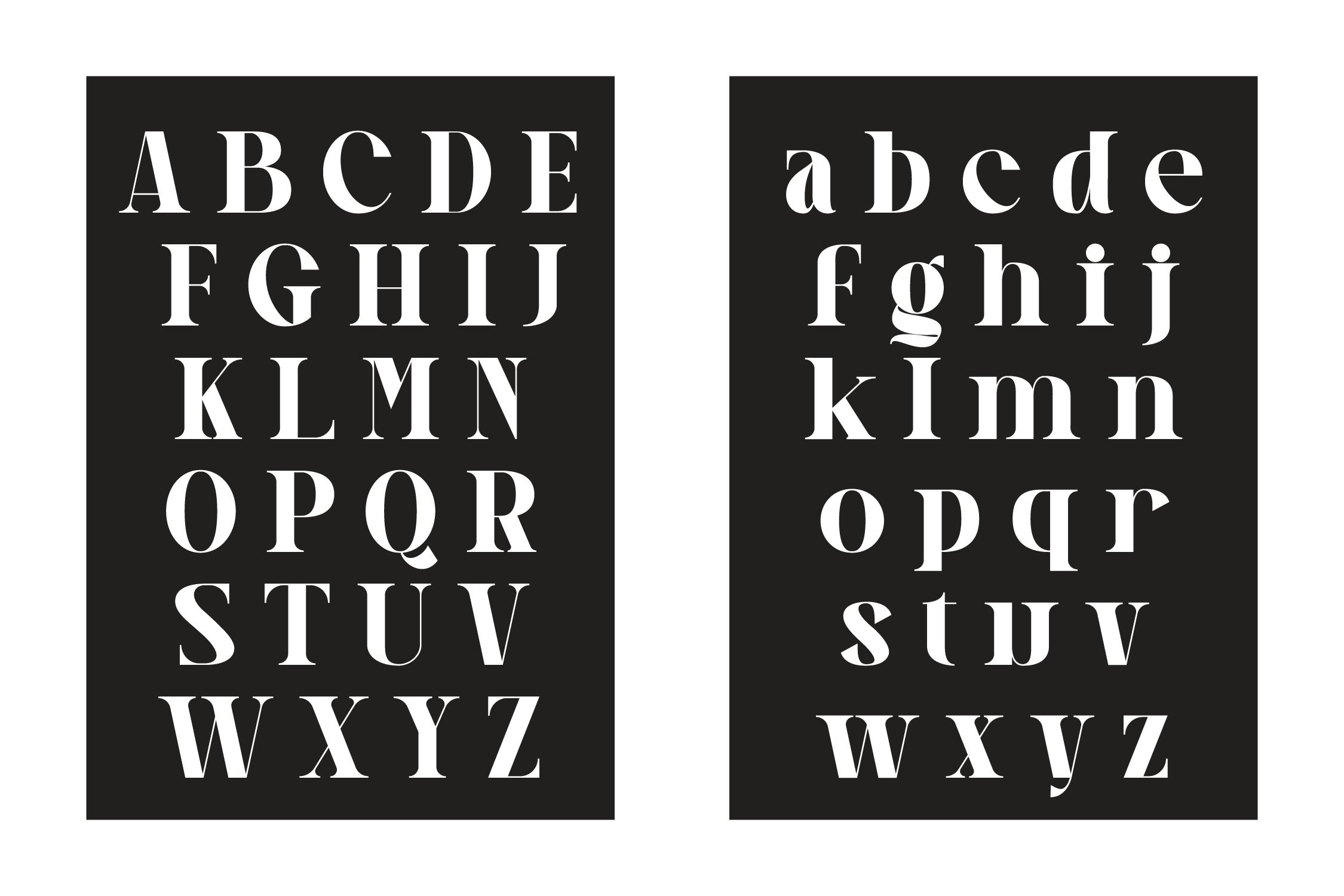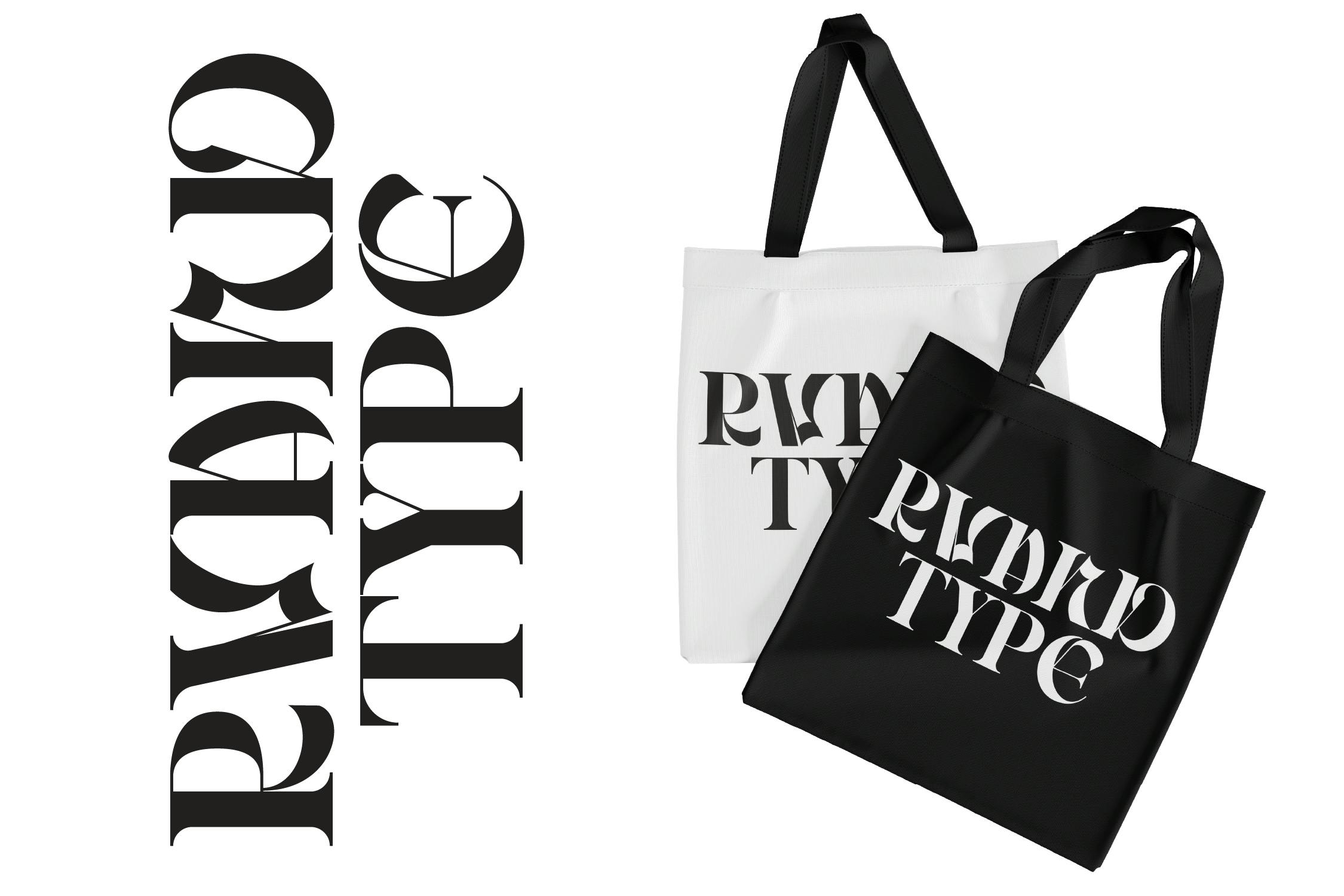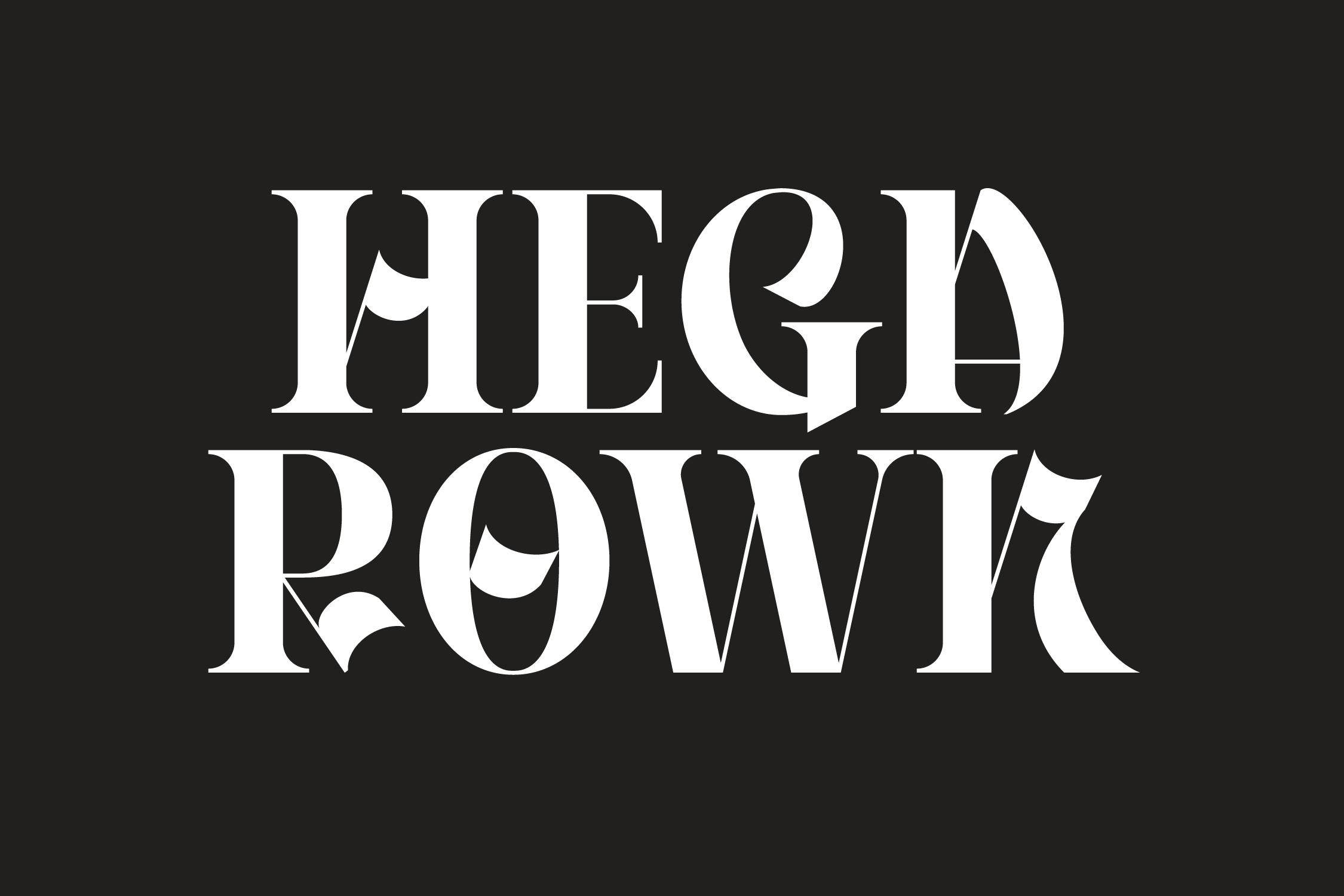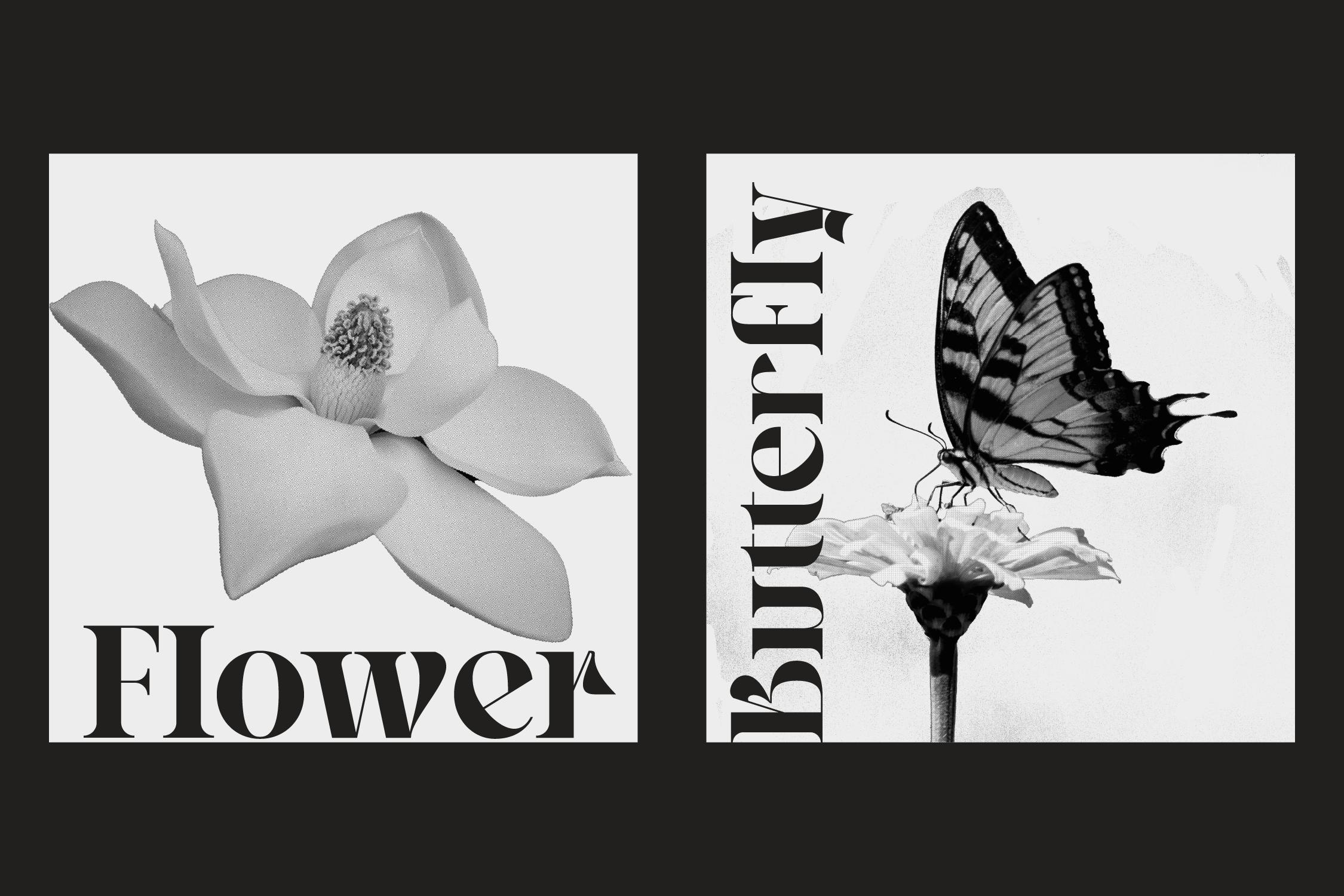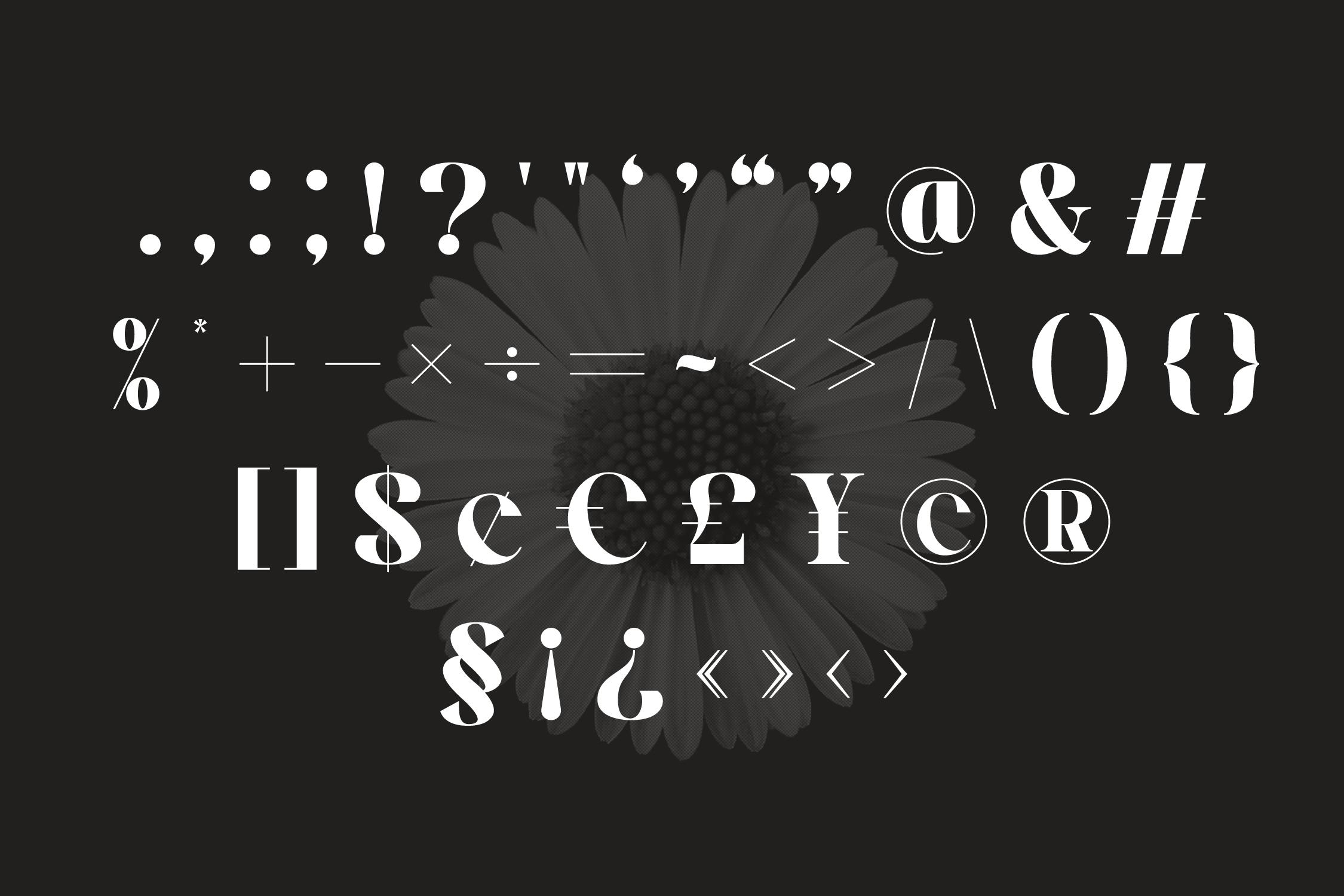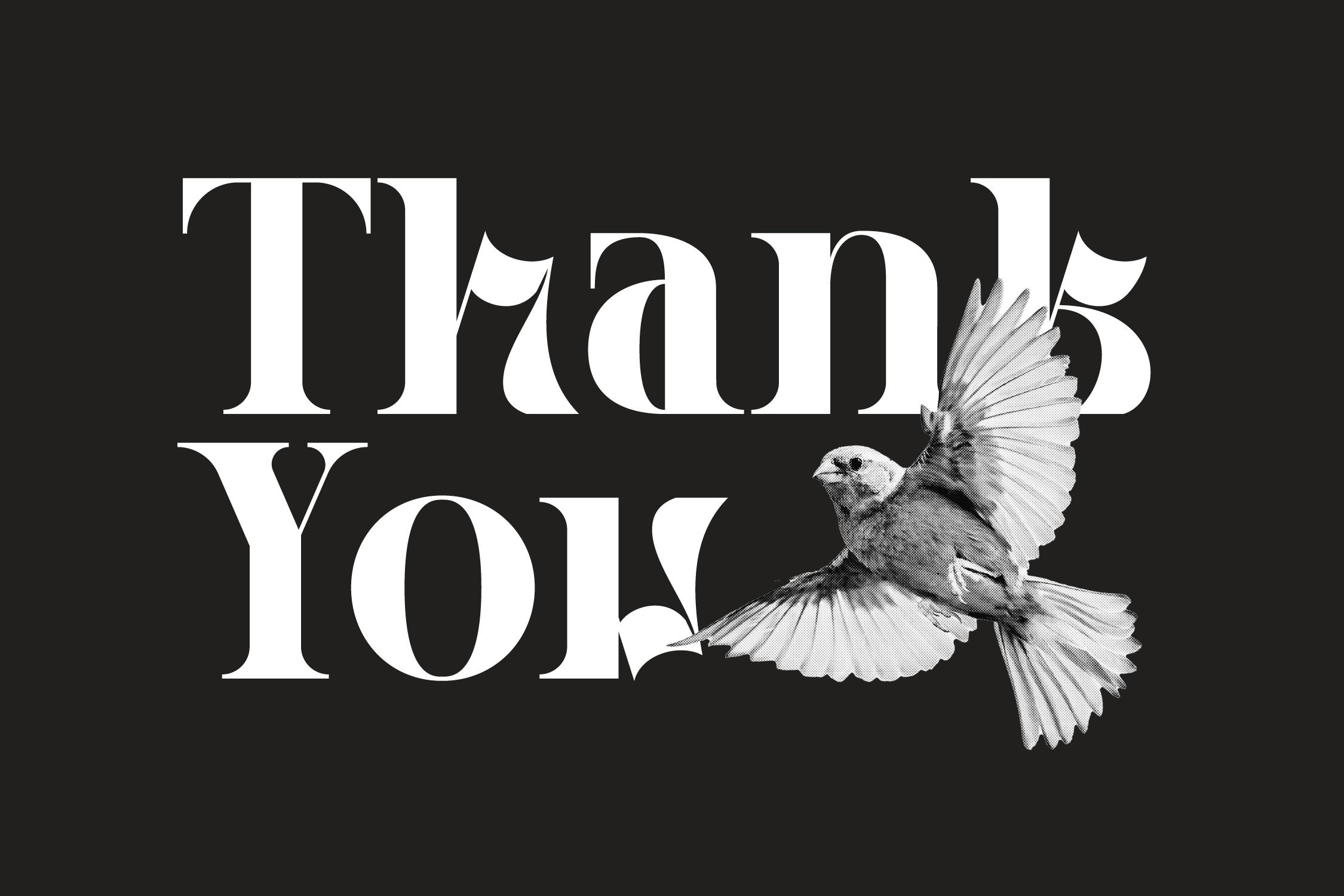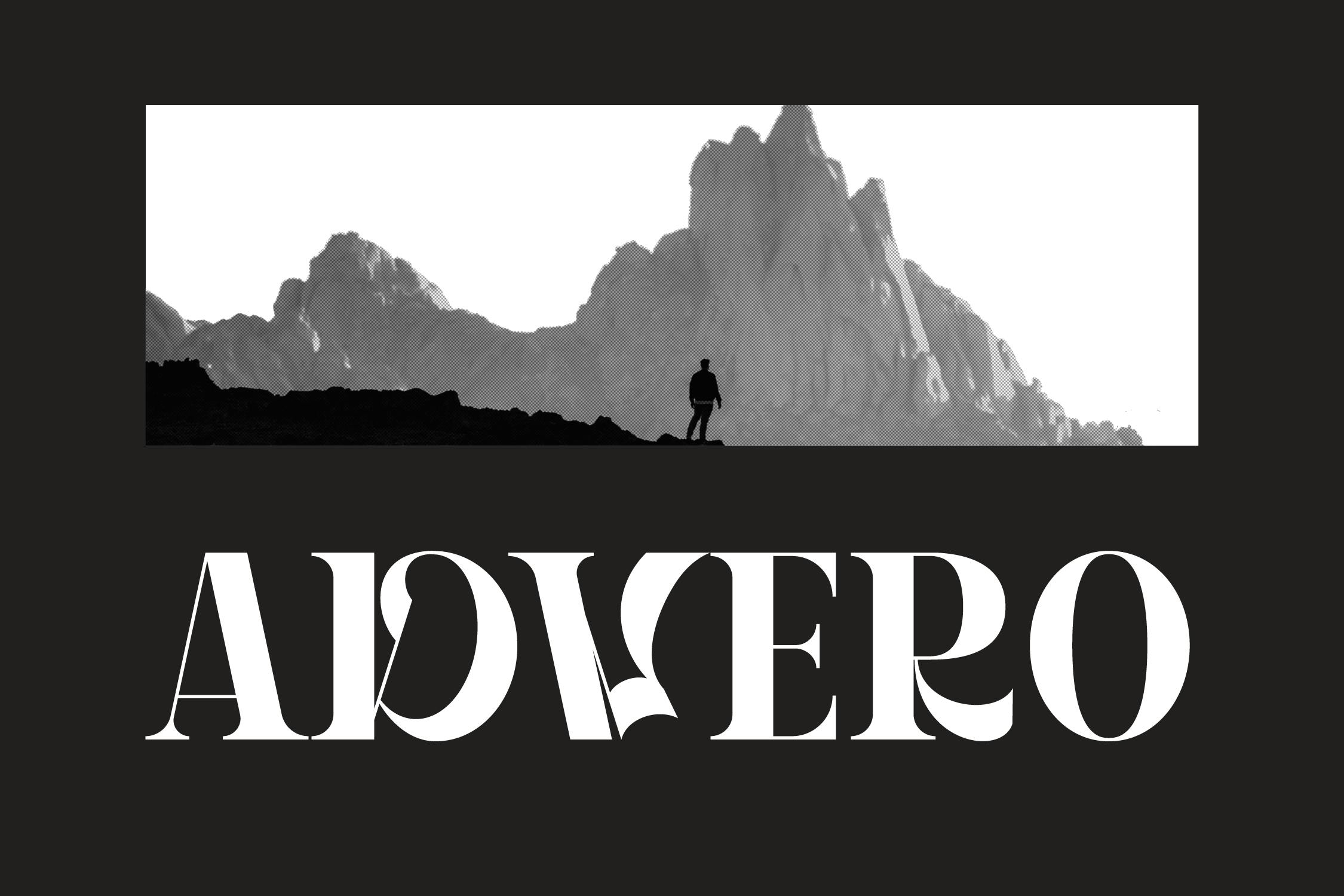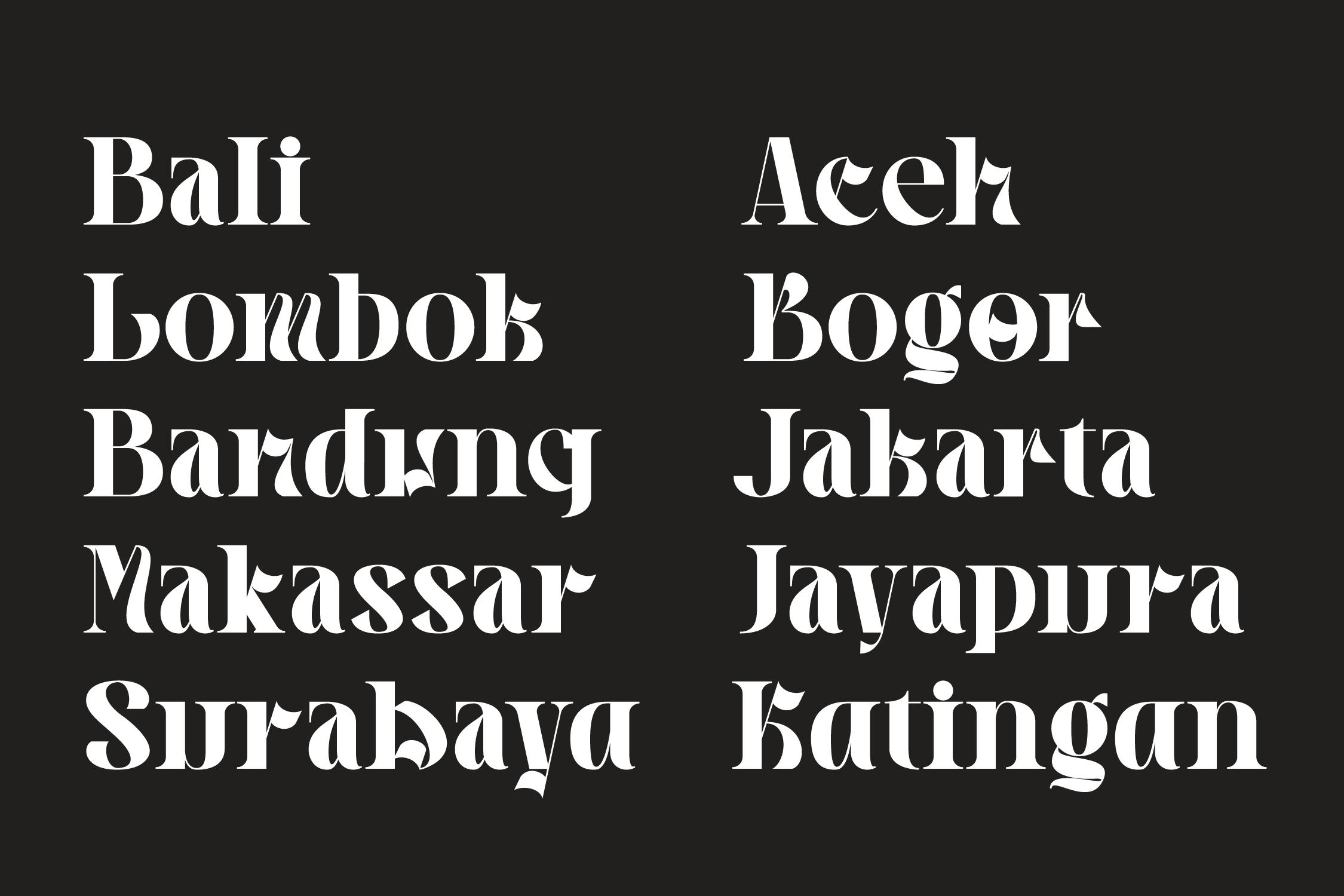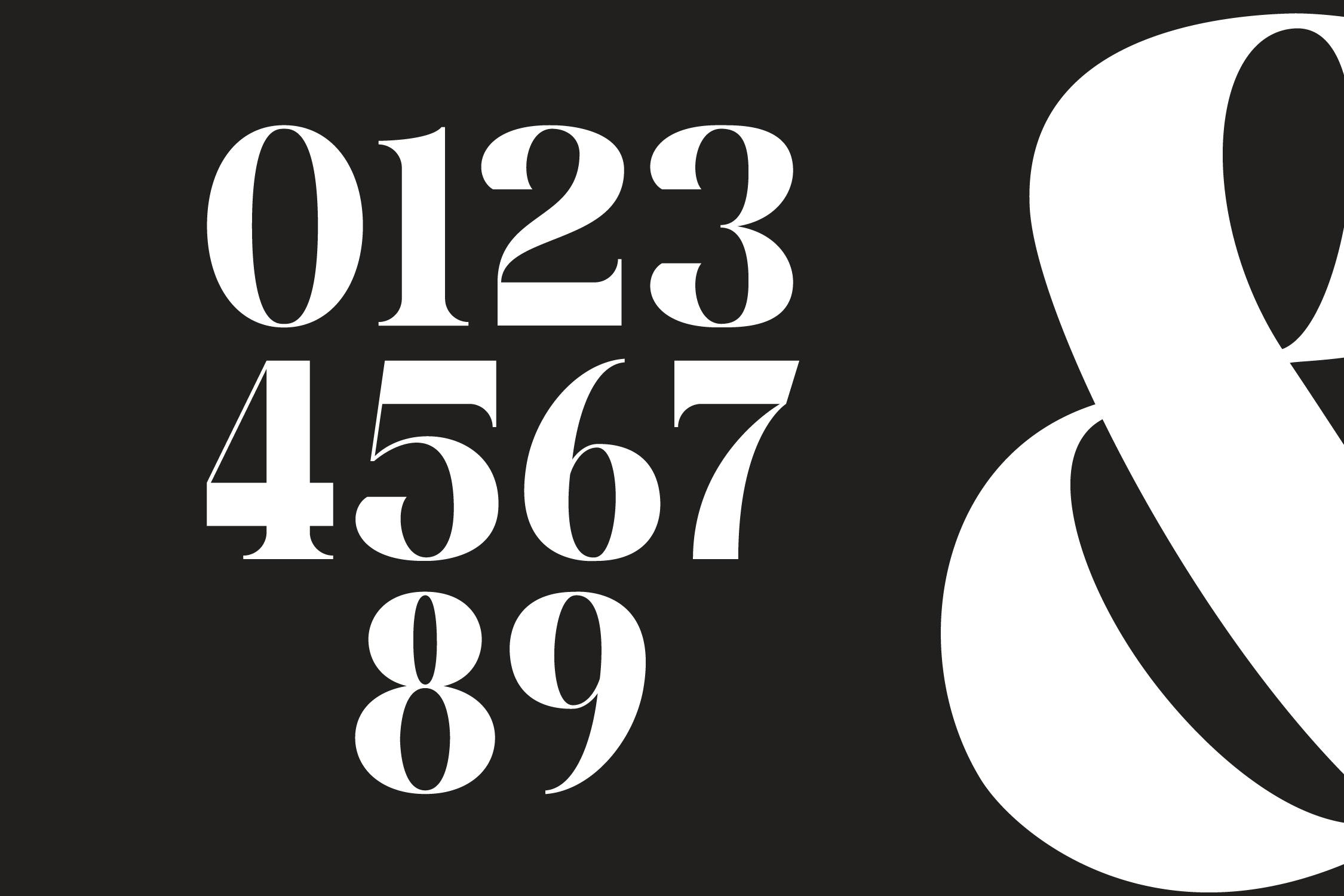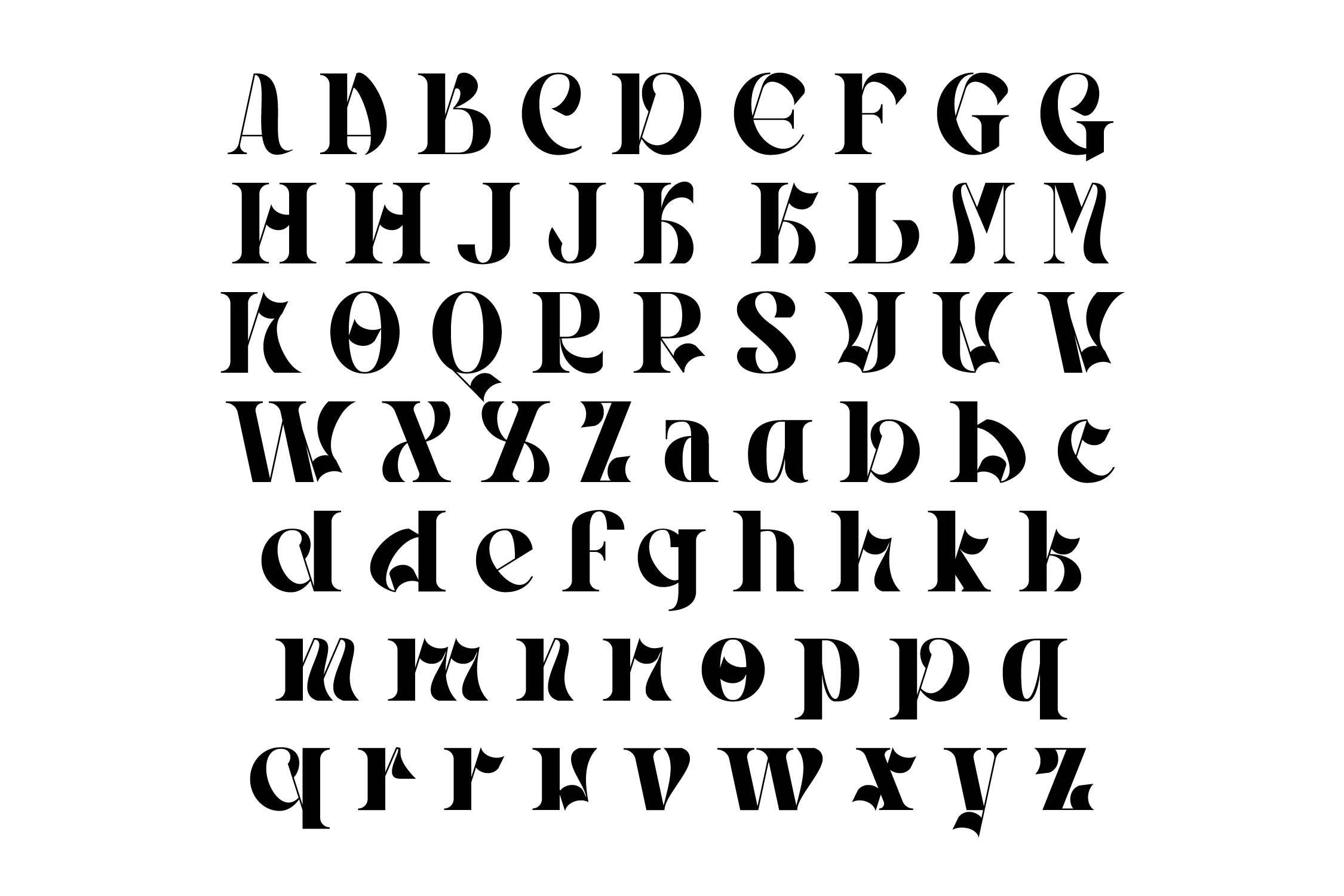
معرفی فونت هگاروان، یک فونت نمایشی جذاب با طراحی مدرن و شیک که آن را به انتخابی ایدهآل برای طیف وسیعی از پروژههای خلاقانه تبدیل میکند. چه در حال طراحی لوگو باشید، چه در پی ایجاد هویت برند، چه در حال ساخت دعوتنامهها، یا طراحی کاغذ یادداشتهای زیبا، فونت هگاروان راهحل مناسبی برای شماست.